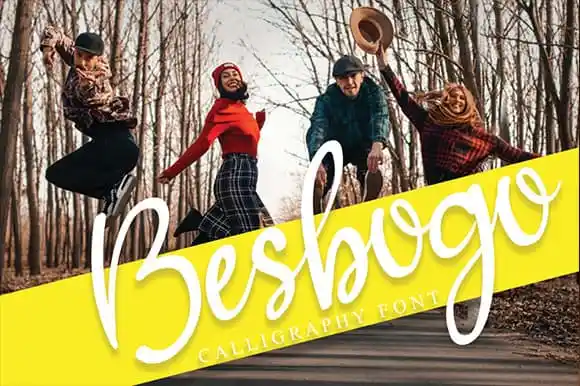
Besbogo Calligraphy Font – Download Grátis
A Besbogo Calligraphy Font é uma nova tendência nas letras tipográficas que se destaca por sua sofisticação e elegância, perfeita para diversificados projetos visuais. Seja em um projeto de wall display, cartas de casamento ou design para publicidade na internet, a Besbogo se adapta com facilidade. Esta fonte é um excelente complemento para embalagens de produtos, ilustrações, logotipos fotográficos e até mesmo marca d’água e design de papelaria. Sua versatilidade faz dela uma escolha ideal para qualquer projeto que exige um toque autêntico e agradável de escrita manual. Ela é o trabalho do designer andikastudio, disponível na categoria Calligraphy Fonts da Alibaba Cloud.